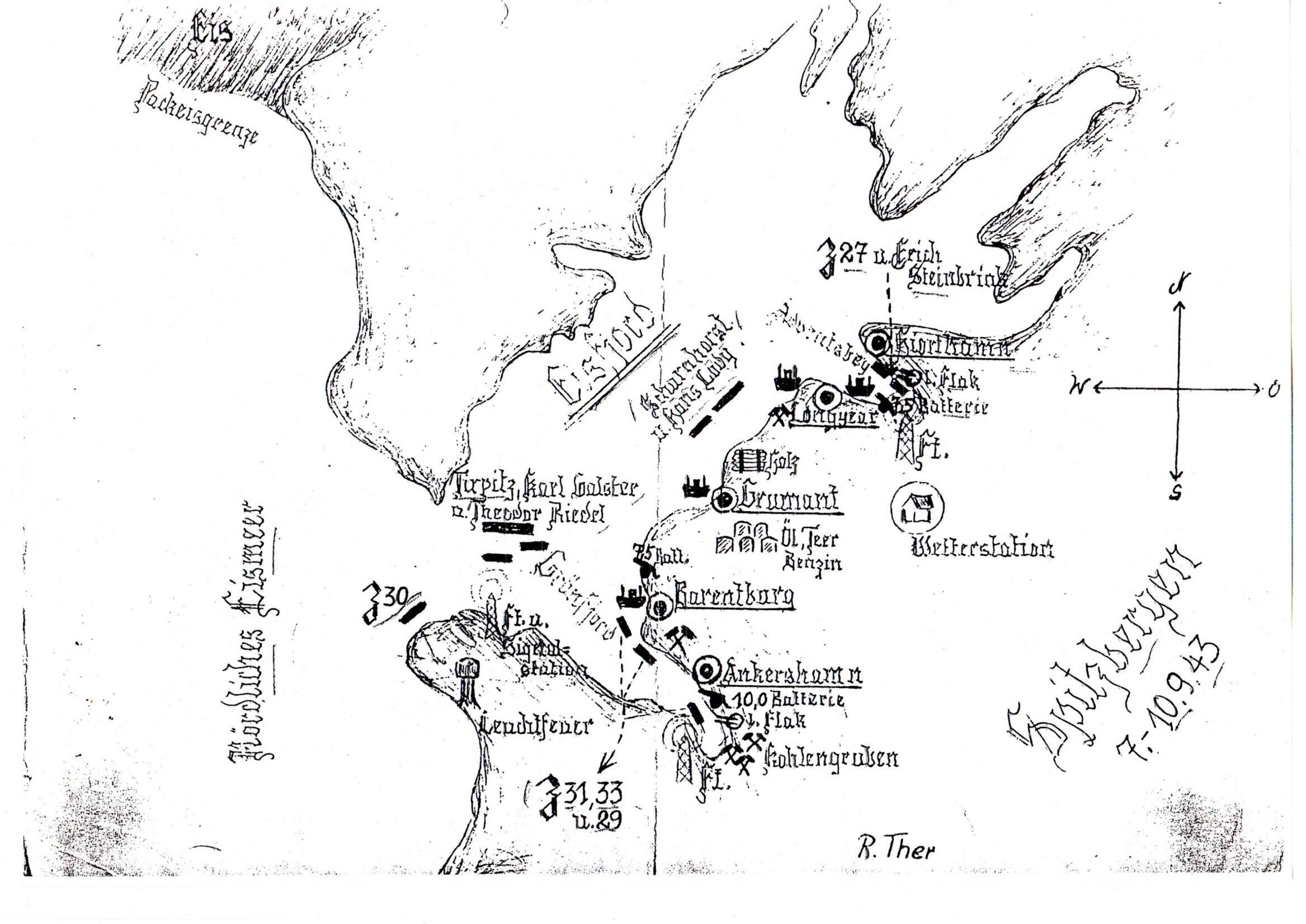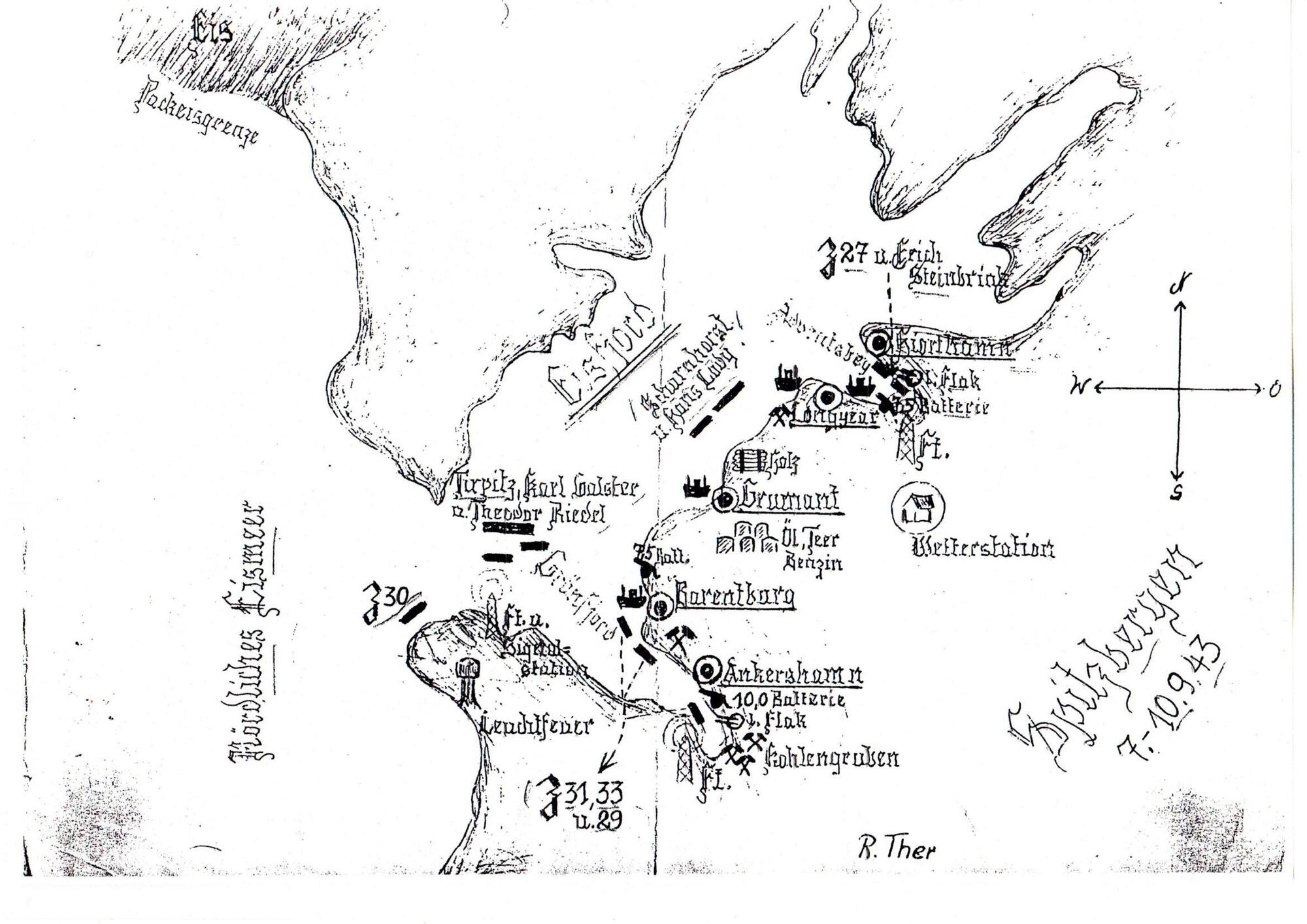
Suche für Schrift auf handgezeichneter Karte die passende Schrift.
hätte eine Frage zu der Schrift auf dem unten angefügten Scan.
Das Original stammt aus dem Jahr 1943 und befindet sich in meinem Besitz, es wurde von Hand gezeichnet und ich habe schon alles abgesucht und durchsucht (Internet) aber keine passende Schrift dazu gefunden.